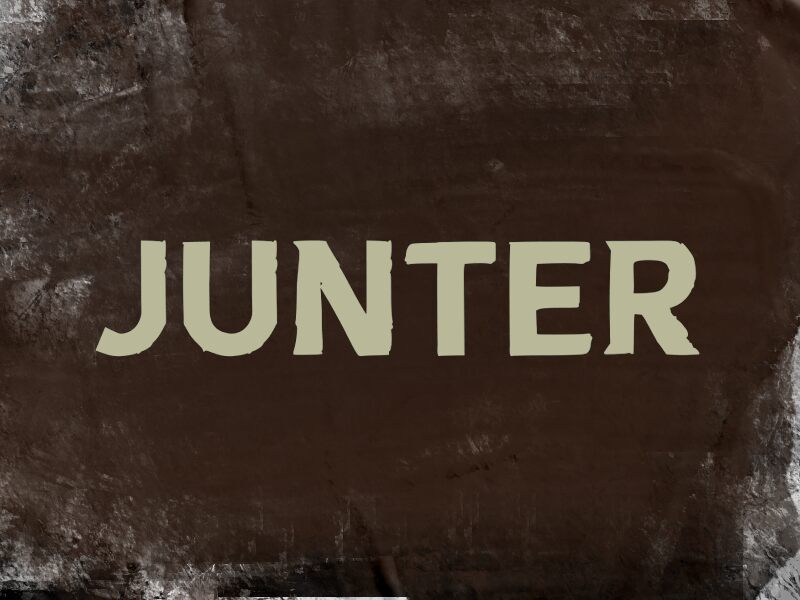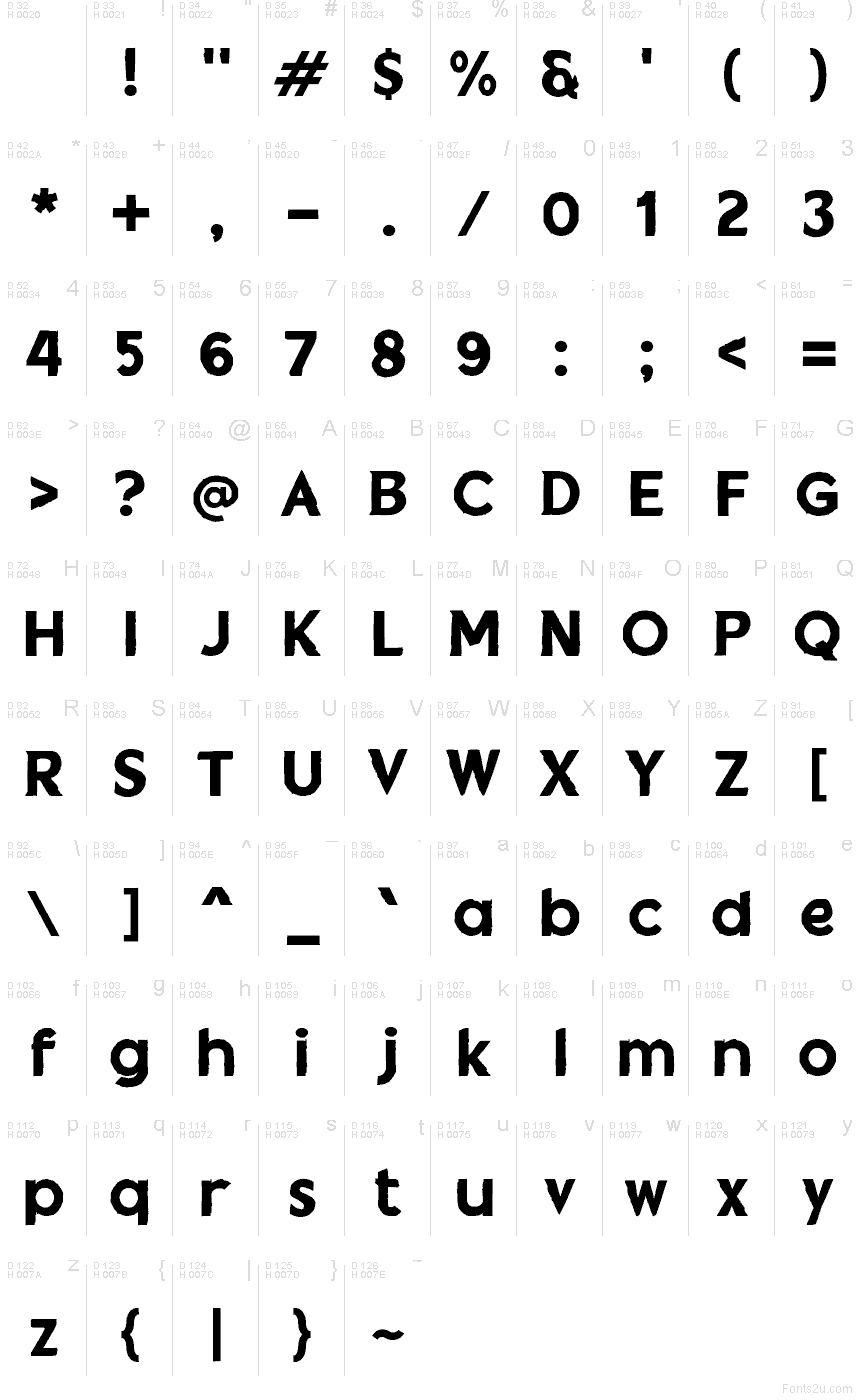
JUNTER
JUNTER od Wep je bezplatné erodované display písmo, ktoré vyniká svojou robustnou blokovou siluetou a hrubými zárezmi, ktoré narúšajú horné časti a hrany písmen. Tento dojem opotrebovania vyzerá, akoby bol do dizajnu priamo vytesaný a nie len aplikovaný, čo písmu dodáva textúru plagátu s ľahko remeselným nádychom.
Skvele funguje na plagátoch ku koncertom, streetwearovej grafike, hororových tituloch, obaloch albumov alebo eventových vizuáloch, kde jeho poškodený povrch hrá dôležitú rolu. Krátke reklamné slogany a výrazné obaly ťažia z jeho hranatého postoja, vďaka ktorému JUNTER zostáva pôsobivý, aj keď okraje vyzerajú otrhane a opotrebovane.